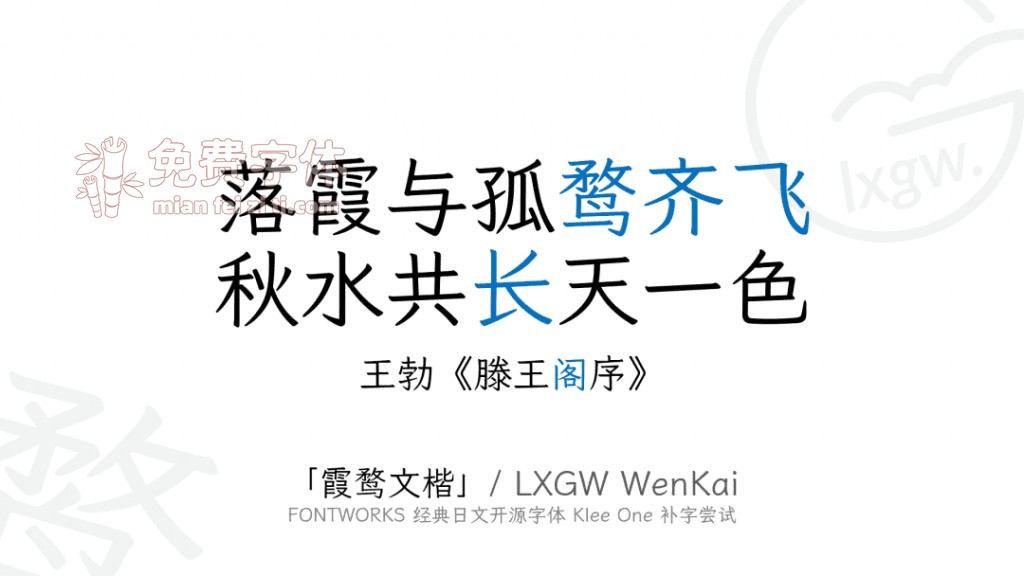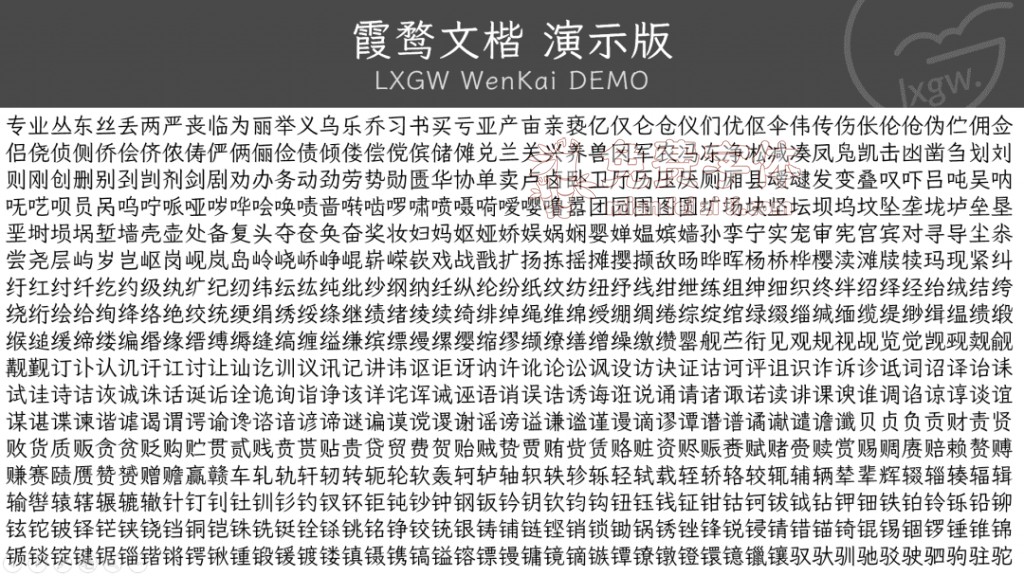
霞鹜文楷是一款基于Fontworks的Klee One的开源中文字体。
前段时间,日本著名字体厂商Fontworks在GitHub上释出了7 款开源日文字体,分别为 Train、Klee、Stick、Rock-n-Roll、Reggae、Rampart 和 DotGothic16。 7款开源日文字体各有各的特点,其中我最感兴趣的,当属 Klee。
这是一款本人非常喜欢的字体,有着日本教科书体的写法,兼有仿宋和楷体的特点,可读性高。一些DIY字体爱好者曾先后用仿宋、刻本仿宋、仓耳今楷补全这款字体,做为手机系统的美化字体移稙在 iOS、Android 等手机系统中,受到很多机友的欢迎。不过这样补全的字体有一些不足之处。
第一,原有字体和后补字体之间有着一定的差异,致使一些不同的文字(如Klee原有汉字与后补简体字)混排之后会有违和感。
第二,由于补字所用的字体(如刻本仿宋、仓耳今楷等)为商业版权字体,补全之后不可用于商业用途,还会有侵权的风险。
鉴于此,本人开始了为Klee这一高质量的日文字体补全简体字的尝试。补全后的字体拟命名 「霞鹜文楷」。选取原字体 SemiBold 字重做为Regular字重。
简体部分
- 补完原字库所含繁体字对应的简化字;
- 补完 3500 常用汉字 ①;
- 修改字形;
- 补完 GB2312 所有汉字。
- 补完通用规范汉字表,若条件允许。
① 包括「现代汉语常用字表」(老 3500 字)及「义务教育语文课程常用字表」(新 3500 字,《通用规范汉字表》一级字表)。
繁体部分
- 补完台湾 4808 常用字 ②;
- 补完 GB/T 12345-90 和 BIG5 一级汉字;
- 补完常用粤闽客字,若条件允许。
② 台湾地区称「常用国字标准字体表」。